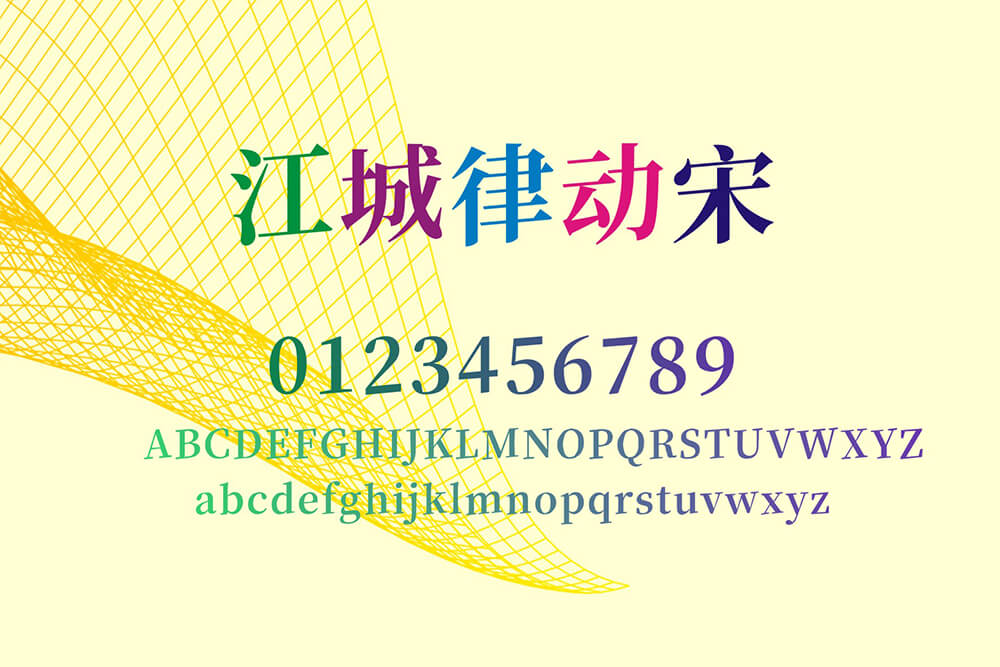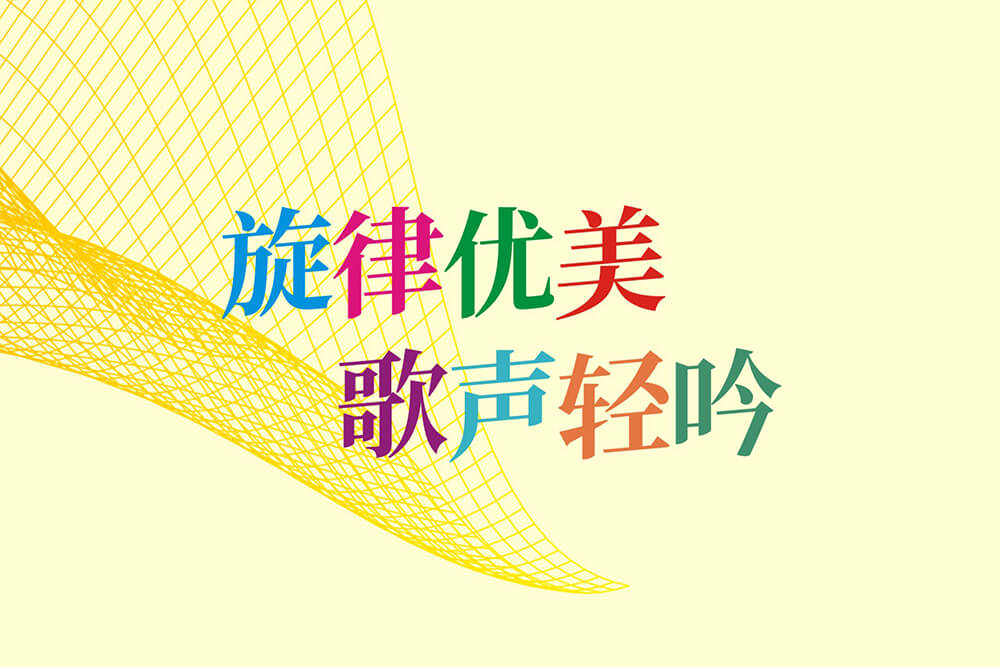
江城律动宋是由设计师刘鹏基于思源宋体 CN-Bold 改造的一款免费可商用的宋体字体。这款字体的特点是将整个字形向左上方倾斜了 5 度,打破了传统宋体的稳重感,使字体带有一种律动感。而思源宋体横细竖粗、衬线、易读性高的特点都得到了保留。
字符集继承了原字体的多语言特性,兼顾简体中文、繁体、日文、韩文、拉丁文及其符号,尤其针对中文使用场景进行了优化,非常适合用于活动促销、广告海报、品牌宣传等场景。